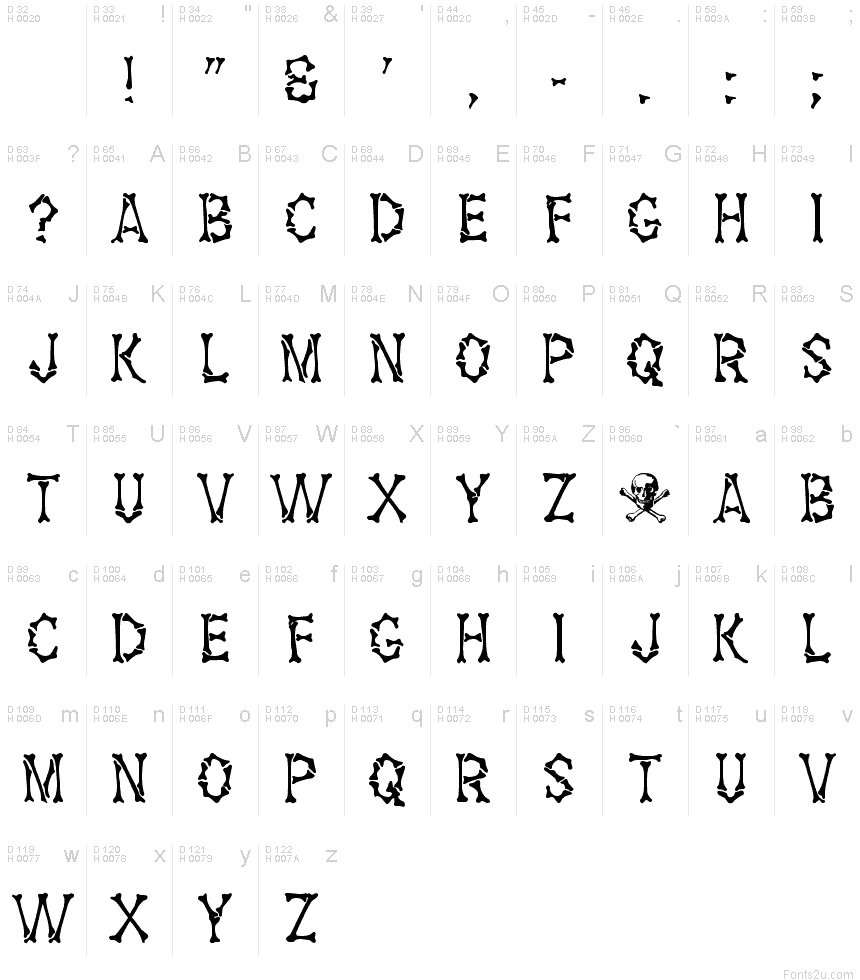
Headhunter, disegnato da D. Rakowski, è un font decorativo gratuito a tema horror che sembra composto da ossa nere e lucide. Ogni lettera appare frastagliata e rituale, con estremità nodose e curve irregolari che donano ai vostri titoli un tocco inquietante e fatto a mano. Il font è abbastanza audace da catturare l'attenzione al primo sguardo, ma mantiene una spaziatura che lo rende perfetto per frasi brevi e titoli incisivi.
Con Headhunter potete dare un'estetica macabra e coerente a case infestate, locandine di Halloween, inviti per feste spaventose, insegne per escape room, copertine di libri horror e grafiche per i social media. Questo font gratuito dà il meglio di sé in grandi dimensioni, dove i dettagli ossei risaltano davvero; abbinatelo a un font sans serif geometrico e pulito per il corpo del testo, così da mantenere la leggibilità mentre Headhunter si occupa di spaventare.